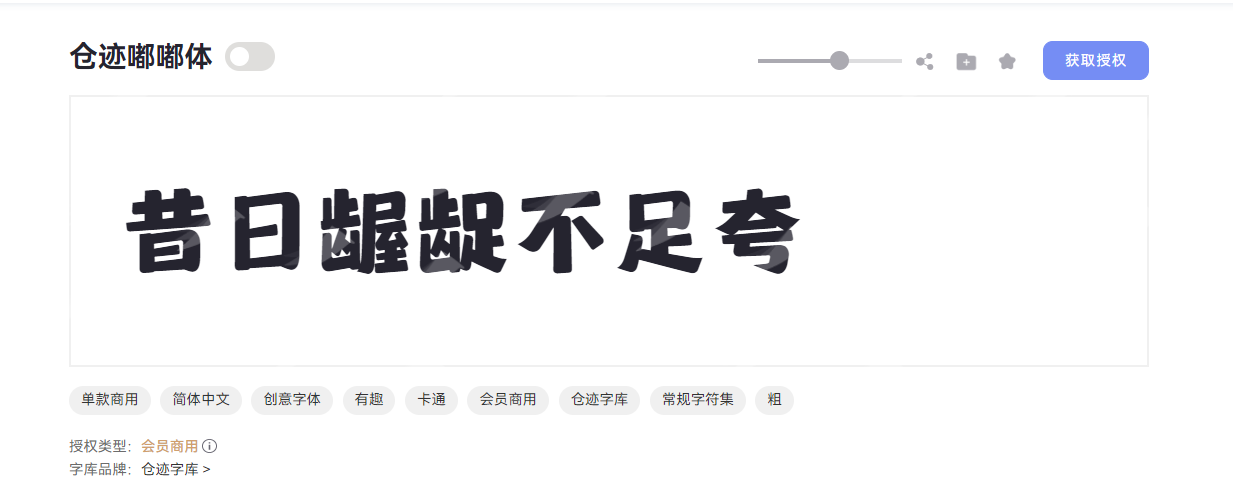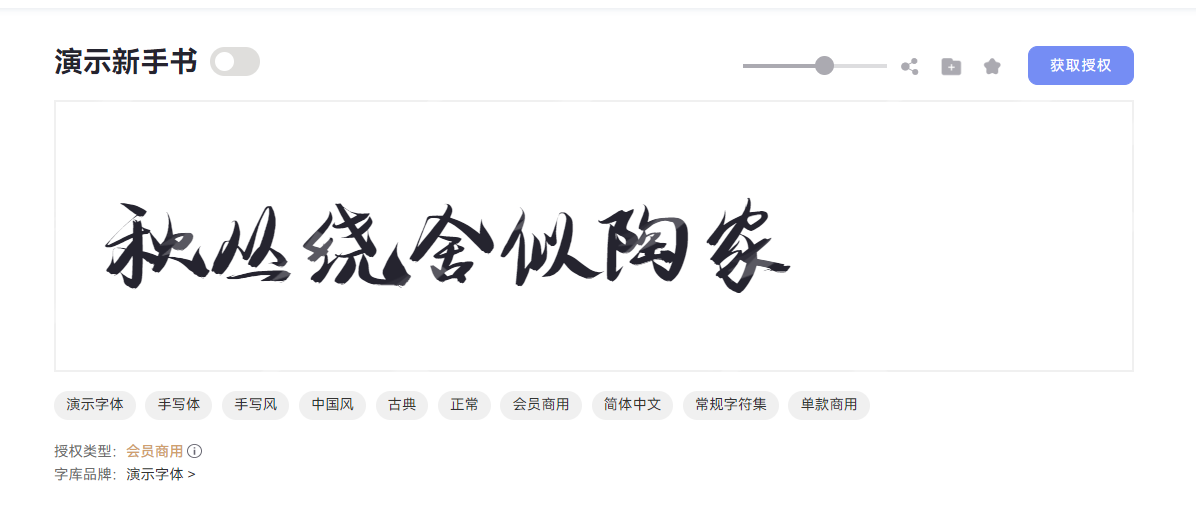
字体设计怎么做出高级感?核心技巧+风格模板推荐
对于设计师们来说,字体往往是作品中不可或缺的存在,是视觉创意的核心部分。一张海报能否吸引到大家的目光,一个品牌 logo 能否第一眼被大家记住,都和字体设计有关系,而字体设计也不是越复杂就越好,过度堆砌华丽的字体设计反而会让作品失去质感,甚至会产生一种廉价感。字体设计想要做出高级感,需要你掌握其中的 4 个核心技巧,并多多了解适配的风格。本文将详细拆解 4 个技巧,并推荐一些字由官网的实用字体模板,帮助你快速找准自己的风格,制作出高级感的字体,新手小白也可以学会哦。
一、字体设计高级感的核心技巧
1.极简留白
想要营造出高级感的字体,从来不会依赖复杂的特效,而是需要用留白来凸显整体设计的重点。留白不是简单的空出一部分画面,而是有意识的对页面进行合理布局,给需要突出的字体留出足够的“呼吸空间”。
举个例子来说,比如像海报上的标题,主标题上下都要留出部分空间,最好是与最近的元素间距空出字体高度的 1.5 倍,避免与副标题、文字、图片元素过于拥挤;或者是品牌 logo 设计过程中,字体周围需要留出30%以上的空白,这样容易让大众把目光聚焦在 logo 本身。
2. 对比平衡
对比平衡就是制造有层次感的视觉张力,一般通过字体的大小、粗细、风格来形成对比,视觉上给大家创造出一种明确的层级关系,同时又要保证画面的和谐。
- 大小对比
主标题的字号与正文的字号比例通常不小于2:1才能形成强有力的视觉冲击。
- 粗细对比
“粗-中-细”这样的结构通常被称为网页设计、杂志设计中的黄金法则。
- 风格对比
比较常用的是“衬线体+无衬线体”的混搭风格,一般不会出错。
需要提醒的一点是,字体的对比是为了建立视觉秩序来突出重点,但是选择的字体通常不要超过3个,否则会适得其反,显得画面很乱。我们需要在字体设计中保持色系、笔画特征的统一。
3. 风格统一
字体设计是为了像观众传递准确的内容,风格统一则意味着字体设计要与该项目的品牌调性、目标受众、传递的情绪高度契合。同时这也对设计师的要求更高,不仅需要为单个的画面匹配合适的字体,更需要为整个项目建立一套完整的字体设计规范,从而呈现出字体的高级感。
如何能做到字体设计的风格统一呢?我经常会用的方法是创建字体风格模板,在一个项目开始之前,了解到该项目整体想要表达的内容,尽可能去收集能代表品牌调性的色彩、物料、图片等,分析它们的共同视觉特征,然后再根据这些共同点去选择匹配的风格。最后设计完成后,务必要在不同设备、尺寸和背景下测试一下字体的可阅读性以及呈现效果,有些不合适的地方再去精细修改。
4. 细节精致
以上技巧都掌握的差不多之后,来到最重要的一步,字体设计的高级感往往藏在“看不见的细节”里,一些微妙的处理就是区分业余设计师和专业设计师的区别,这需要大家慢慢去摸索。
我觉得有几个经典的细节维度可以供大家参考一下:
- 字间距行距
默认的间距一般偏紧,高级感的设计可以适当加宽字间距,尤其是大写字母和标题,标题字间距一般在50-100.对于正文来讲,1.5倍行距是观众比较舒适的阅读体验。
- 笔画的处理
最直观的是观察“O” 、“S”的曲线是否流畅自然。如果你选择的是衬线体,仔细看衬线末端的形状是尖锐还是圆滑;如果是手写体,需要根据画面调整,保留适当的墨迹感和粗细对比。
- 色彩与质感
常规的黑色字体太过死板,建议可以使用深灰色,视觉效果上会更加柔和和高级。
二、高级感字体设计模板推荐
1.仓迹嘟嘟体
仓迹嘟嘟体是由仓迹字库推出的创意字体,以卡通有趣的风格在设计领域备受青睐。这款字体的笔画粗细均匀,字形偏方正,笔型融入大量圆润设计,直线中巧妙点缀圆角,形成很明显的方圆对比平衡,即保留了字体的力量感,又增添了几分柔和。另外,很符合高级感字体设计的就是笔画处理细致,圆头笔画与自然连笔过渡,让每个字都独具形态,笔画边缘干净利落,没有模糊毛躁的问题出现。仓迹嘟嘟体最具代表性的“勾”笔画,形似胖乎乎的小脚,小巧灵动,为字体注入俏皮活力。
2.演示新手书体
这款演示新手书体很适合用于国风类的设计,它笔画之间存在大量断笔、空隙,保留了手写体的笔触间隙,同样也避免了字形的拥挤,符合极简设计的核心技巧。这款字体最值得推荐的就是对比平衡运用的恰到好处,笔画粗细过渡自然,墨色浓淡变化也非常自然,而且较为复杂的字通过这种笔画的粗细对比形成了很好的视觉层次,提升观众的阅读性。
3.Ryujin Attack 字体
Ryujin Attack 是一款充满张力的手写风英文字体,以手写风、涂鸦与豪放为核心风格。它的字间距行距都有充足的留白,中宫宽博的设计让字符间留有呼吸感,既保证了可读性,又不失大气与灵动。大家可以着重学习一下这款字体对于墨色浓淡的过渡,没有生硬的色块跳跃,很想毛笔的真实质感,再加上它的笔画粗细均匀却不失力量感,每一笔都似随性挥洒的涂鸦笔触,让这款字体完美展现了自由不羁的涂鸦艺术感以及细腻的书法韵味之间的碰撞。
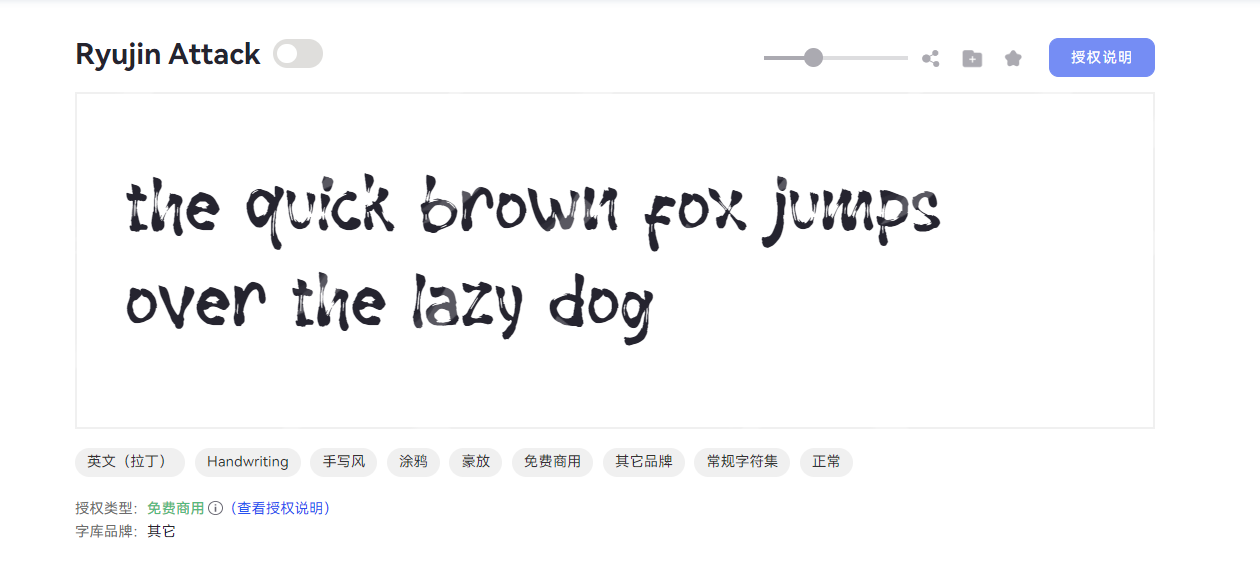
4.演示佛系体
演示佛系体一款自带禅意气质的特色创意字体。字体采用居中重心设计,配合宽博中宫,让整体形态稳重大气又不失舒展。笔画均采用圆润的毛笔笔触,没有尖锐棱角或者突兀的粗细变化,笔画风格统一。独特的笔画断开处理是其点睛之笔,在连贯的视觉节奏中留出巧妙呼吸空间,打破沉闷的同时更显灵动层次。